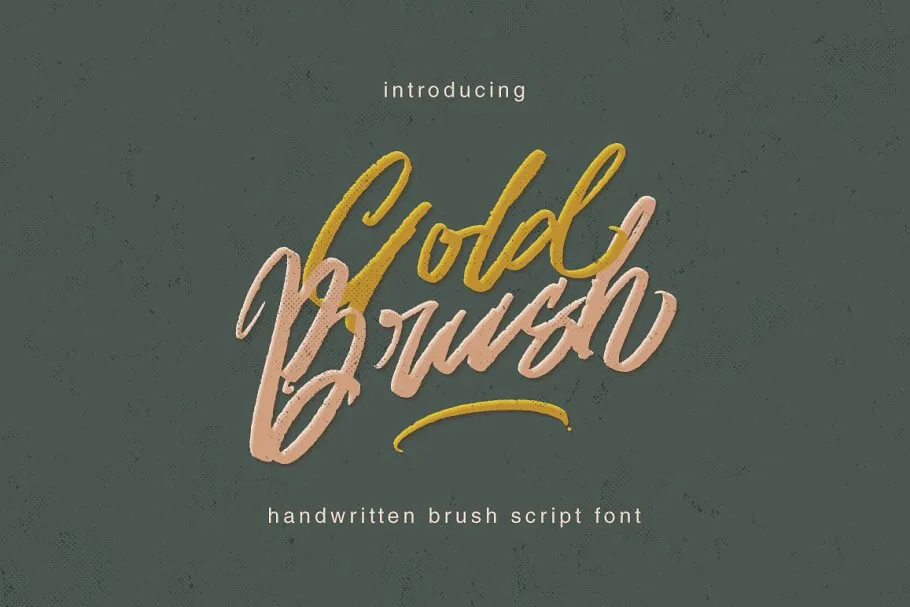
Gold Brush Font
Aqui está uma versão descritiva de 2 parágrafos curtos para a página de download da font “Gold Brush Font”: Bem-vindo à nova adição da nossa seleção de fontes: a ‘Gold Brush Font’. Esta elegante e fresca fonte script foi projetada com designers em mente, ideal para estilos mais criativos e arrojados. Ideal tanto para marcações imponentes quanto para aplicações de design gráfico pessoal, esta font oferece um equilíbrio perfeito entre graça irregular e elegância, sem perder sua relevância no cenário atual das práticas digitais. A ‘Gold Brush Font’ é perfeitamente adaptada a vários tipos de projetos. Seja para aplicativos de marcação ou design de produtos em pacotes de embalagem, este estilo irá brilhar sob qualquer formato. E não importa qual outra fonte você estiver usando ao seu lado: essa ‘Gold Brush Font’ oferecerá uma sobreposição visual atraente e moderna que complementará perfeitamente suas criações. Esse é um novo elemento que adicionará sofisticação e criatividade aos seus projetos. Aproveite para explorar os limites de sua imaginação, enquanto mantém sempre essa ‘Gold Brush Font’ à mão em seu arsenal de design.